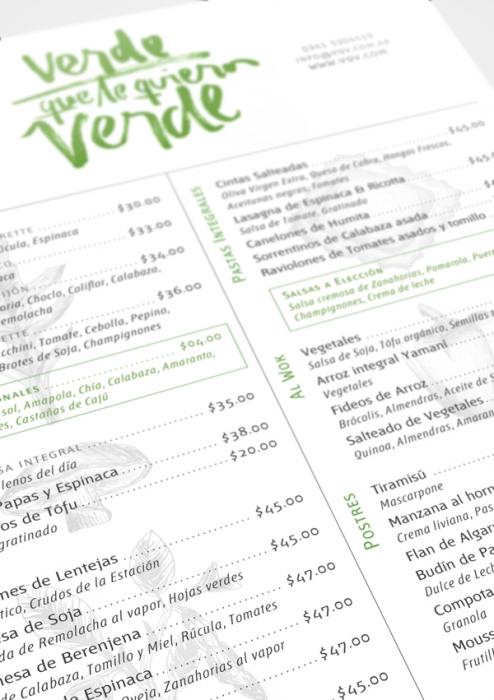
Schrift gesucht ... Wer kann weiterhelfen?
kann mir einer von euch weiterhelfen und sagen um welche Schrift(en) es sich handelt? (s. Bild)
The logo is done by hand. All characters are shaped different
Any more  info on where the picture is from?